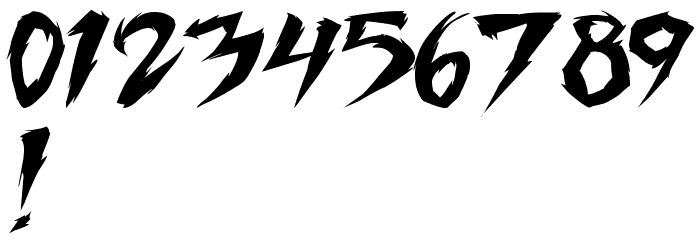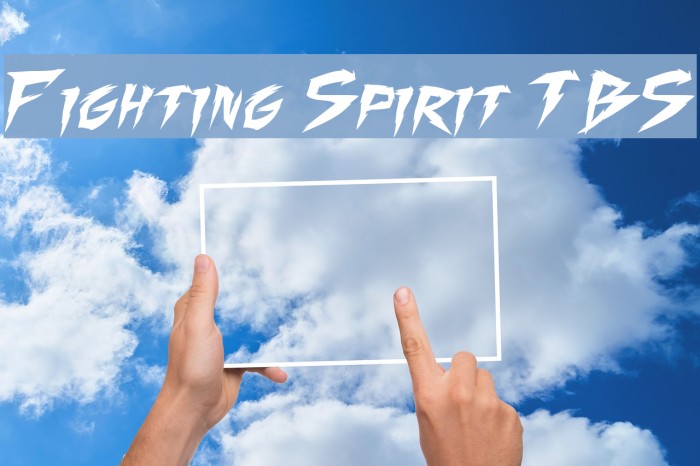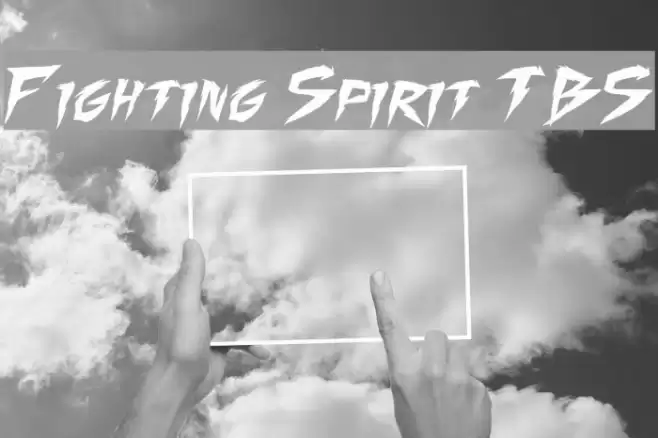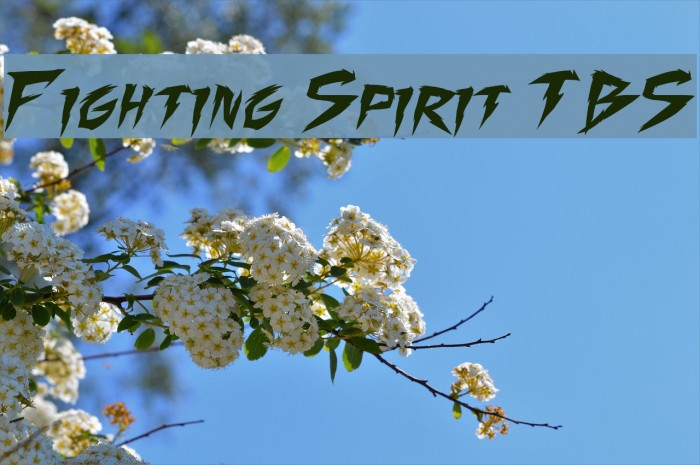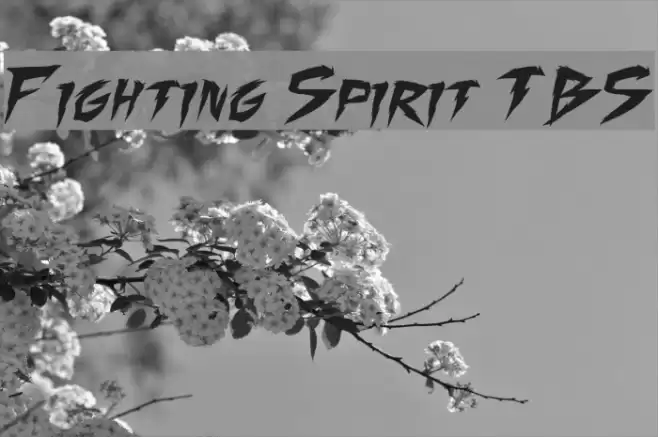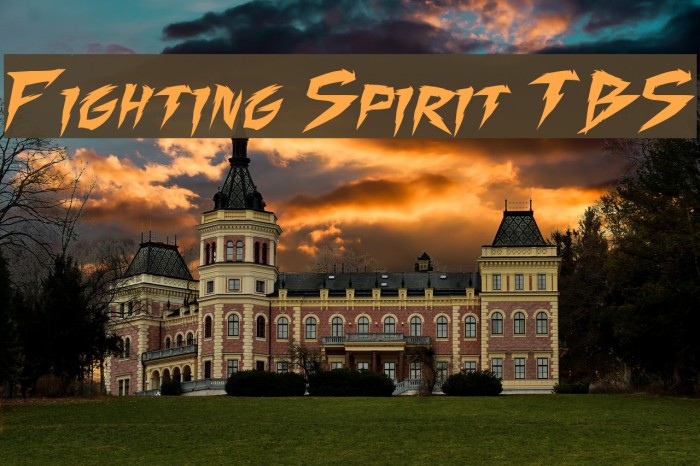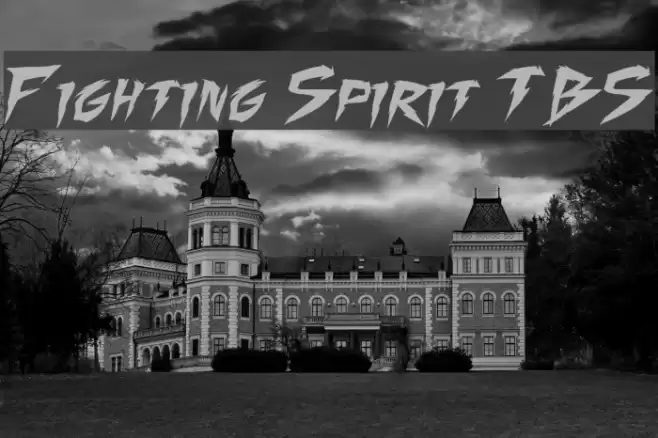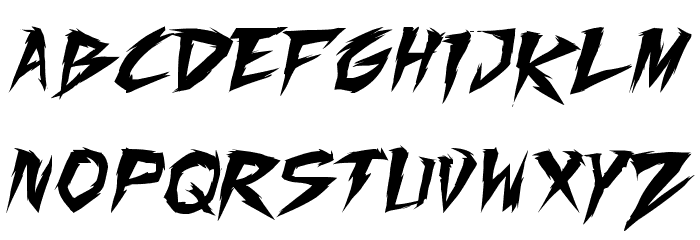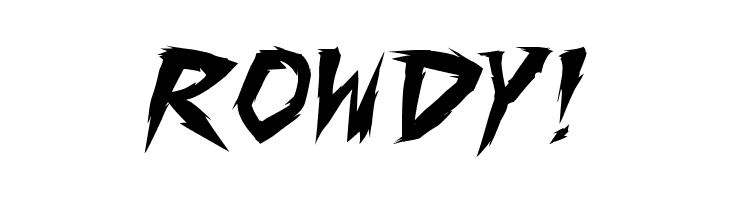
Fighting Spirit TBS Font
| Proiecte propuse | Ideal for sports branding, action movie posters, video game titles, and any project needing a bold, energetic typeface. |